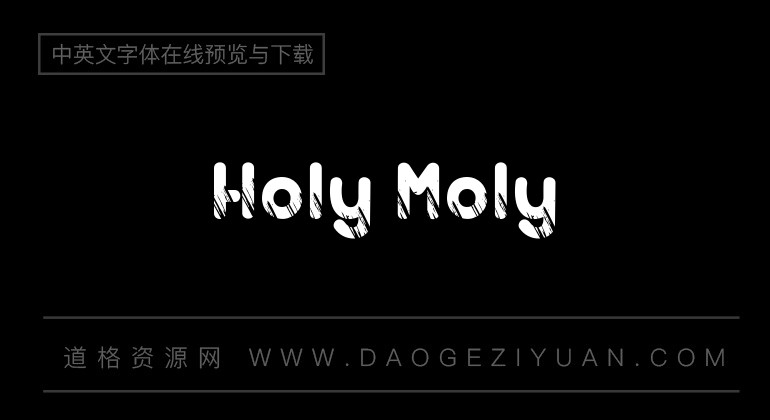
Holy Moly
Holy Moly是一款免费的手写体字体,由设计师Monica Ramos设计。该字体受到了传统和现代设计的影响,具有可爱的手写风格,使用它可以创造出美丽而又现代的设计。它可以用于各种个性化的设计,包括海报、卡片、商标、标题等。它还可以用于社交媒体,如Instagram、Facebook等,以及印刷品上。
Holy Moly是一款非常不错的手写艺术字体,具有很好的视觉感,适合于文化类的宣传设计、商业类品牌的广告和产品包装设计以及个性化文字排版等较多场景。